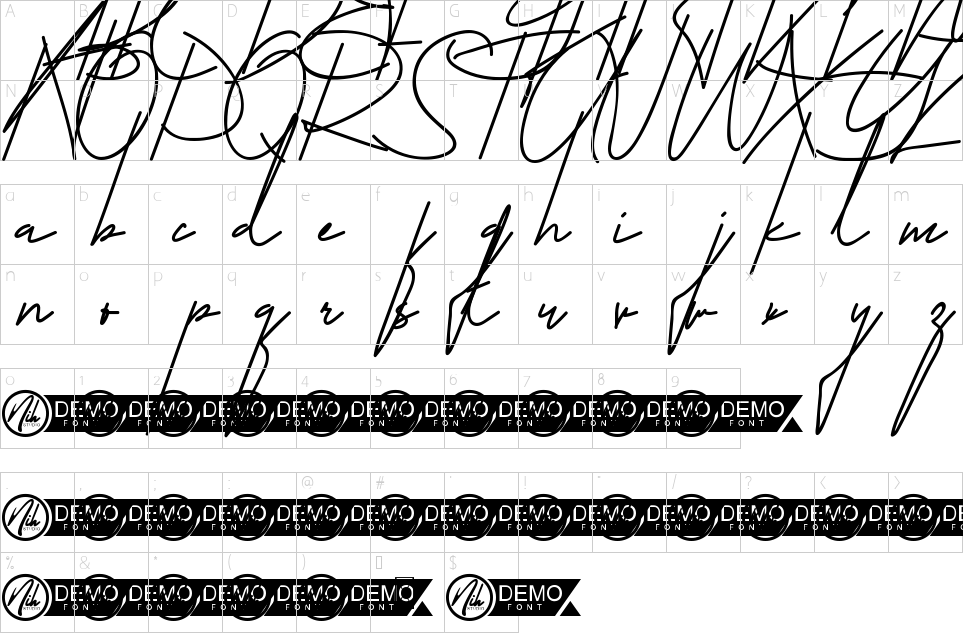
Descubra a Akselia, uma fonte moderna e sofisticada, ideal para qualquer projeto gráfico. Desenvolvida por NihStudio, Akselia oferece um equilíbrio perfeito entre elegância e simplicidade. Suas linhas fluidas e arredondadas criam um equilíbrio atraente, tornando-a uma excelente escolha para design de materiais gráficos, como identidades corporativas, flyers e cartazes. A Akselia é uma fonte de alta qualidade que pode ser facilmente adaptada para diferentes tamanhos e contextos, proporcionando uma experiência de usabilidade agradável. Se você está procurando por uma fonte de uso livre e moderna, Akselia é uma ótima opção. Descubra agora e experimente a diferença de qualidade e elegância que a Akselia pode trazer para seus projetos.